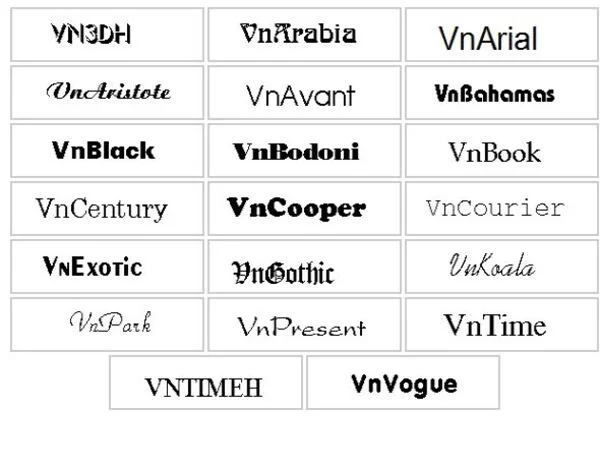
Khi thiết kế, hẳn các designer đã từng một lần gặp các lỗi font, không đọc được. Những lúc này, các nhà thiết kế nên tải font chữ VNTime về để hỗ trợ. Bộ font VNTime là bộ font chữ sang trọng, tinh tế được Việt hoá trên máy tình và cung cấp cho người dùng nhiều kiểu chữ khác nhau, tương thích với bộ gõ tiếng Việt. Vì vậy, hôm nay Printgo xin giới thiệu sơ lược về font VNTime và gửi đến các bạn file download VNTime miễn phí để tải về và sử dụng.
Font VNTime là một font chữ Việt được sử dụng rất phổ biến. Khi sử dụng font chữ này, người dùng phải sử dụng bảng mã TCVN3 - bảng mã dành cho những font chữ có dấu chấm và chữ VN đứng đầu.
Font VNTime cũng là một font chữ được sử dụng rất nhiều tại Việt Nam vì nó có rất nhiều ưu điểm. Các phần mềm gõ tiếng Việt như Unikey, Vietkey sẽ tương thích với font VNTime. Không chỉ vậy, bộ font này còn có thể sử dụng với các trình soạn thảo văn bản phổ biến hiện nay, do vậy khi download font TCVN3 về máy tính người dùng sẽ được hỗ trợ thêm font chữ với những loại văn bản khi tải xuống từ Internet.